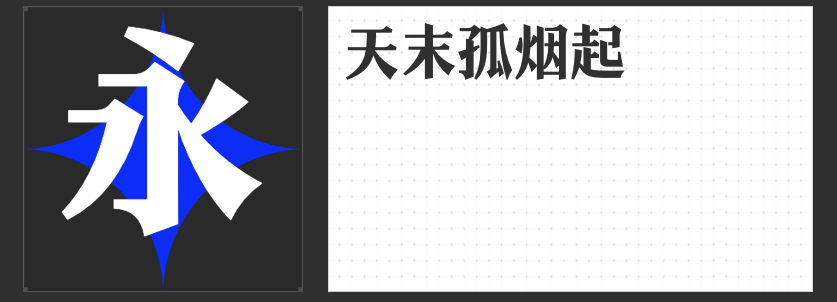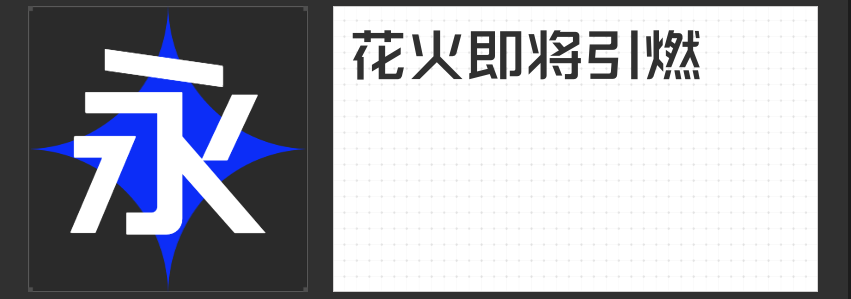
怀旧风情,字体里的时光印记 —— 四款经典怀旧字体推荐
在这个数字化时代,文字不仅仅是信息的载体,更是情感与记忆的桥梁。今天,让我们一同走进四款充满怀旧感的字体世界,感受它们独特的韵味与魅力,让文字成为连接过去与现在的纽带。
这款字体以其无衬线的简洁设计,搭配粗壮有力的笔划,瞬间抓住你的眼球。它的撇捺圆润不尖,横直均匀,既易于阅读,又极具视觉冲击力,是标题、导语及标志设计的理想选择。每一次使用,都仿佛在诉说着坚韧不拔的故事,让人心生敬意。
2.云书法三行魏碑体
一笔一划间,透露出古朴的韵味,云书法三行魏碑体以其工整而不失灵动的楷书形态,展现了古风之美。笔划严谨而朴厚,整体字形柔和流畅,风格朴拙中不失险峻,流畅中蕴含力量。无论是用于标题还是正文,都能营造出一种穿越时空的文化氛围。
3.励字粗圆简繁
字面宽大,结构方正饱满,励字粗圆简繁以其独特的圆润笔形和粗壮笔画,传递出端正大方的气质。这款字体既保留了传统书法的韵味,又融入了现代设计的简洁明快,适合用于各类需要展现稳重与亲和力的场合。
4.字圈也字山海明朝
字圈也字山海明朝,宋体的柔美与黑体的硬朗完美融合。通过对衬角装饰的精心优化,以及笔画形态的调整,这款字体既大气端正,又不失趣味性。它既能满足标题字对于醒目易读的需求,又能在正文排版中展现其独特的韵味,是兼顾理性与感性的设计佳作。
这四款字体,每一款都承载着不同的历史情感与文化记忆,它们不仅仅是文字的呈现,更是时间的见证者。在追求设计美感的同时,不妨让这些充满怀旧感的字体,为你的作品增添一抹独特的文化色彩。